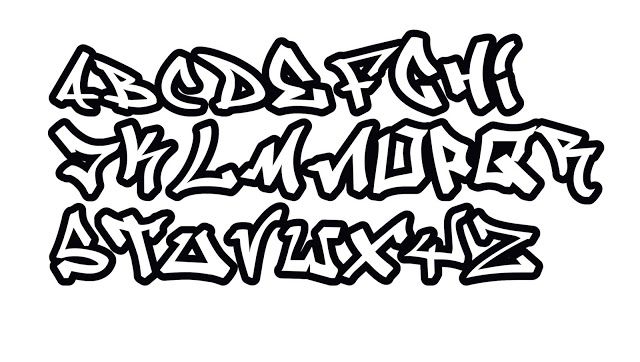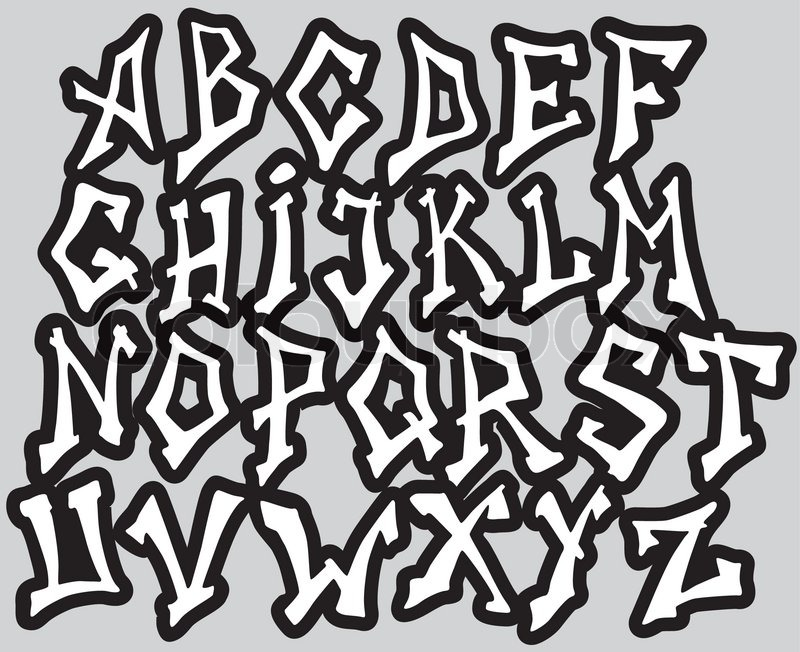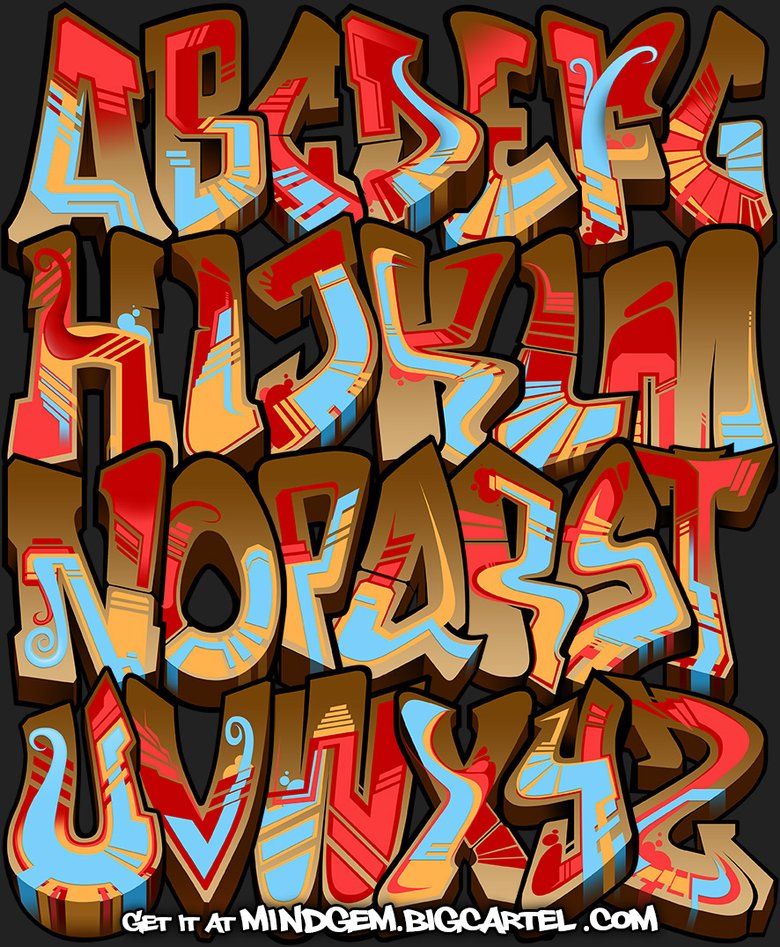
Шрифты для фотошопа граффити русские: Граффити шрифты — русские скачать бесплатно
Русские граффити шрифты для фотошопа. Семь кириллических шрифтов граффити
About Graffiti Fonts
Graffiti is usually appeared as graphics or lettering scratched, scrawled, painted or marked in any manner on property. Graffiti has existed since very ancient times in Ancient Greece and the Roman Empire. In ancient Rome, people don’t have a photocopier or a fax machine or newspaper, and when you have a written message to let other people know, you scratched it on a wall. In modern times, however, graffiti is considered illegal in a lot of countries. But a country that with significant tradition in graffiti is Brazil and Sao Paulo, one of the largest cities in Brazil, is considered to be the current center of inspiration for graffiti artists.
Graffiti can have different styles. Tagging is the simplest type of graffiti, usually done quickly in spray paint, markers or pens and lacking artistic form; A throw-up involves more work than tagging, usually having two or three colors and done in bubble letters; Stenciling can be a quick way to produce more complicated graffiti designs and by using two or more layers, you can produce color-rich designs; Wildstyle is a form of graffiti that was made popular by graffiti artists like Tracy 168, Zephyr in NYC.
Depending on your preferences, there are many fonts that can be used for graffiti purposes such as bubble fonts, stencil fonts , outline fonts etc. However, for complicated graffiti styles, they can never be achieved by fonts. Graffiti fonts can be a good way to study graffiti letters or graffiti alphabet, but you really should learn to express in your style. Get inspired and check out our collection of free graffiti fonts , or use our graffiti text generator below.
Многие райтеры имеют свой стиль и придумывают самостоятельно . Но все равно существуют основные принципы и шрифты, которыми пользуется большинство.
Я тоже иногда придумываю свои буквы и зарисовываю их на бумаге, во-первых, чтобы не забыть, а во вторых, воспроизводить на стене знакомый шрифт потом легче, чем изобретать что-то на ходу.
Самые распространенные стили написания и буквы граффити
Баббл
Такие мультяшные объемные буквы – самый распространенный вариант. В шрифте баббл буквы должны сливаться и как бы наплывать друг на друга. Единственный минус – иногда прочитать, что написано в этом стиле довольно трудно, так как буквы могут искажаться практически до неузнаваемости.
“ Estou enviando minha primeira fonte e espero em breve contribuir mais para o crescimento da undial шрифт вклад в типографику (мы пытаемся перевести без Google, поэтому приносим извинения, если ошиблись). Его прямое вдохновение — бразильские граффити, Бразилия — родина дизайнера Брока Маркеса. В Бразилии много ярких граффити, поэтому этот шрифт должен был быть в нашем списке.
19. Graffonti
“ Три взаимосвязанных семейства шрифтов в стиле граффити, стили Graffonti включают в себя: атомную бомбу, трехмерную каплю и градиентную заливку.